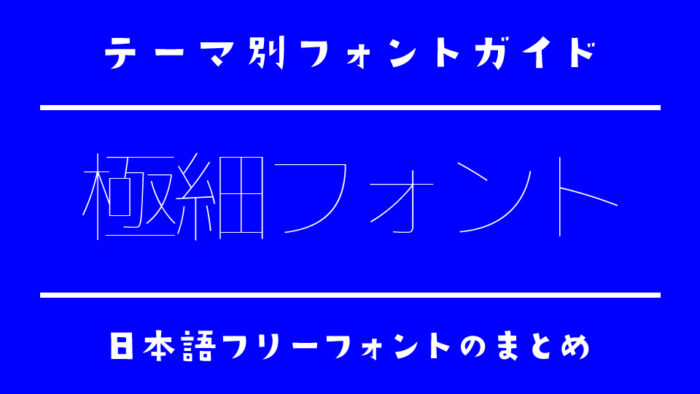
今回は、繊細でスタイリッシュな印象を与える「極細ウェイト」の日本語フリーフォントをご紹介します。
極細のラインは、空気のような軽やかさと、凛とした美しさを併せ持ち、シンプルな中にも上品さを演出してくれます。ミニマルなデザインや洗練された印象を求める場面にぴったりです。
今回は、そんな極細ウェイトの中でも、可読性とデザイン性を兼ね備えたフォントを厳選しました。ポスターやWebデザイン、名刺などのアクセントとして、ぜひ取り入れてみてください。
「極細ウェイト」のおすすめフォントまとめ
以下のサンプル画像は本記事で紹介している一部ですが、「極細ウェイト」をもつフォントをまとめてみました。
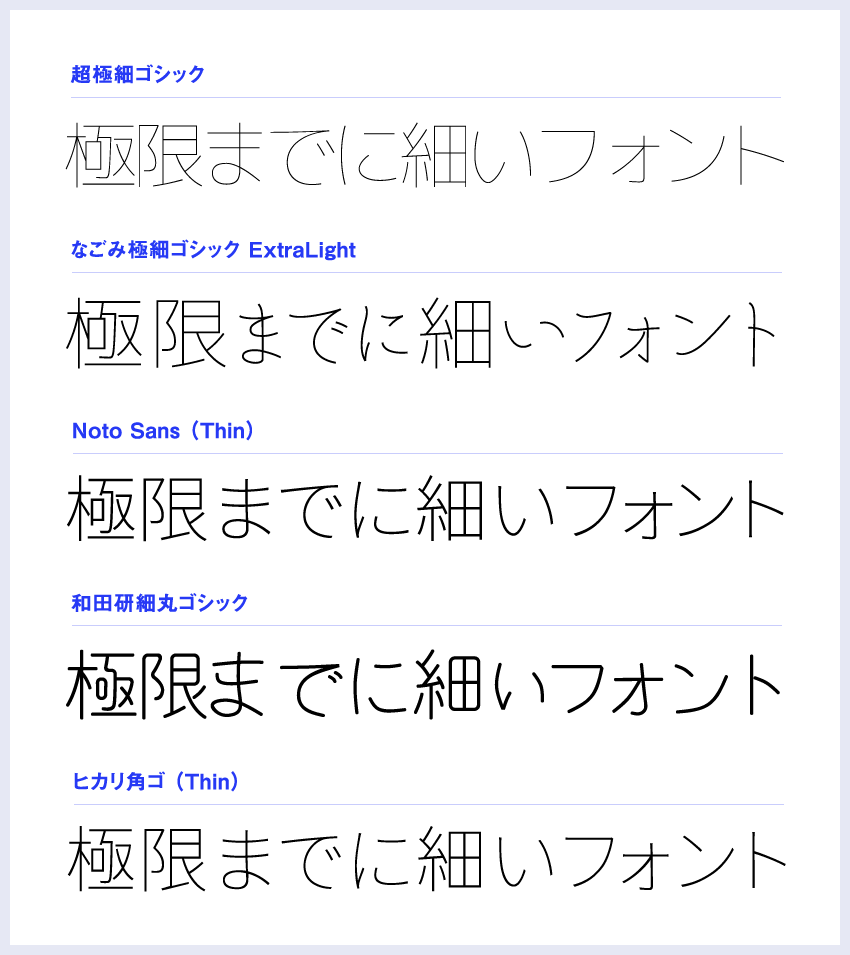
超極細ゴシック
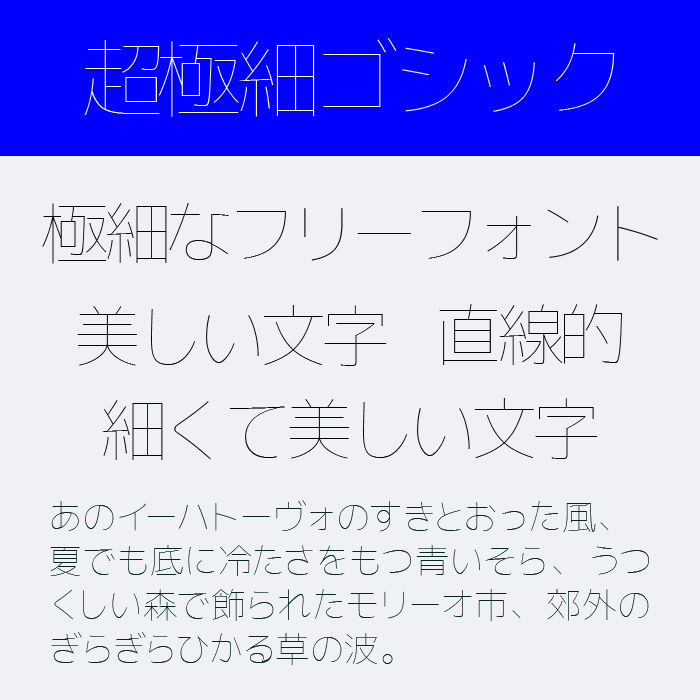
超極細ゴシック体フォントは、「超極細」を目的としてボールペンを使い定規でなぞって書いたようなイメージに制作されているゴシック体フォントです。
Noto Sans(源ノ角ゴシック)
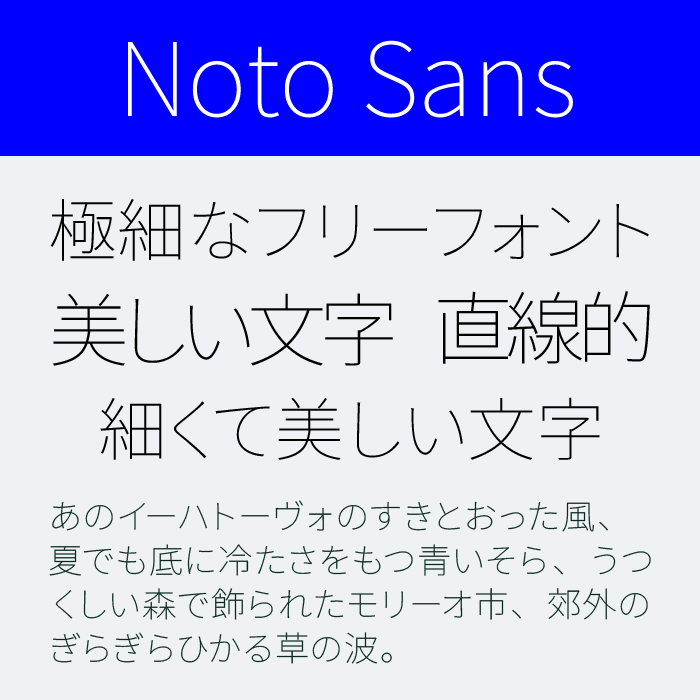
Noto Sans(源ノ角ゴシック)フォントは、GoogleとAdobeが協力して開発したベーシックな角ゴシック体フォントです。
世界中のあらゆる言語に対応することを目標に開発されているため、可読性や視認性に非常に優れているフォントです。一番細いウェイトが「Thin」ですが、可読性が優れてスタイリッシュな雰囲気あるフォントです。
ヒカリ角ゴ
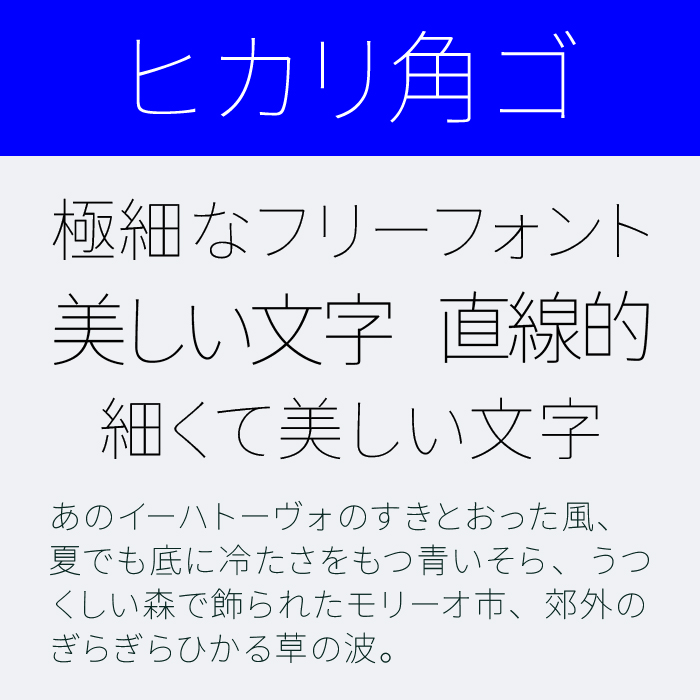
ヒカリ角ゴフォントは、上記の源ノ角ゴシック(Noto sans)をベースとして、ふところを狭く、漢字をより平らかになるように調整されたゴシック体フォントです。
ふところが調整されている分、直線的で機会的なクール雰囲気を感じるフォントです。
M PLUS
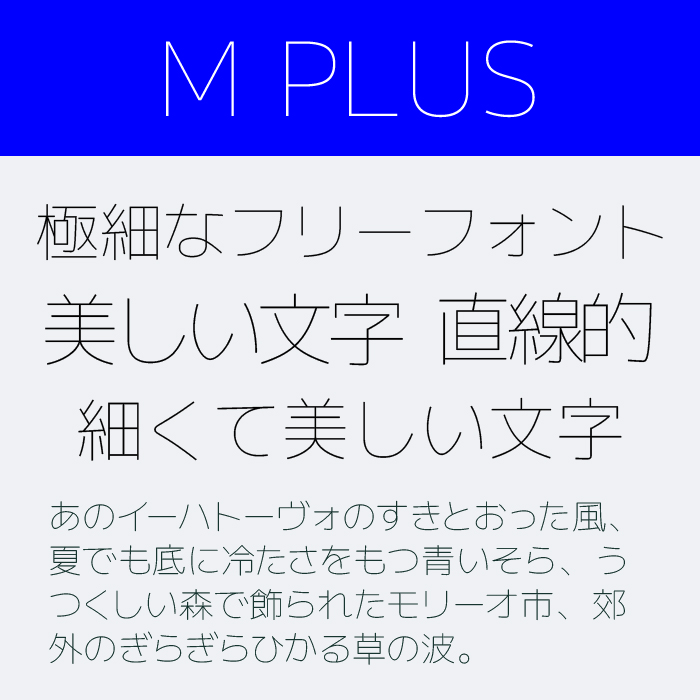
M PLUS(M+)フォントは、直線と曲線のメリハリがきいて、少し丸みがありカッチリしすぎていない、使いやすいモダンな角ゴシック体フォントです。ウェイトが9種類あり、一番細いウェイトが「Thin」です。
トガリテ
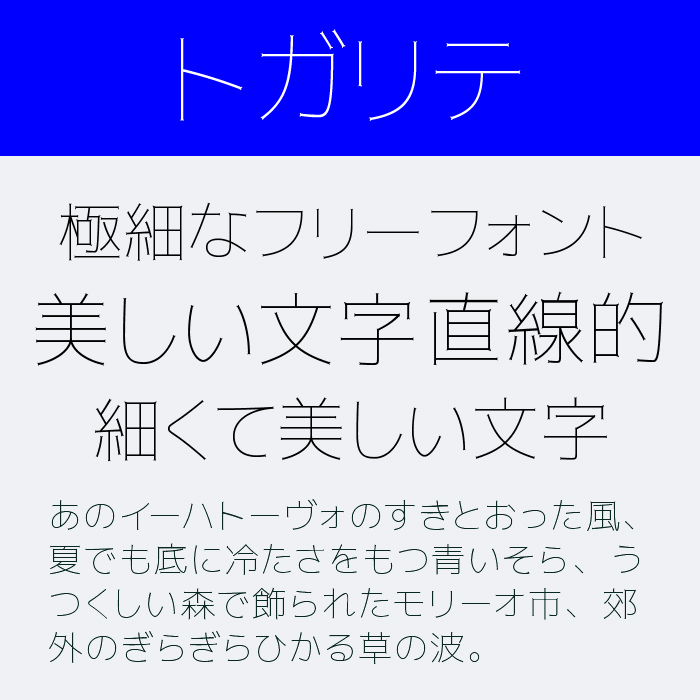
トガリテフォントは、文字の先端にトゲトゲの装飾が施されているフォントになっています。細いですが、線先に装飾が施されている可愛らしいフォントです。
和田研細丸ゴシック
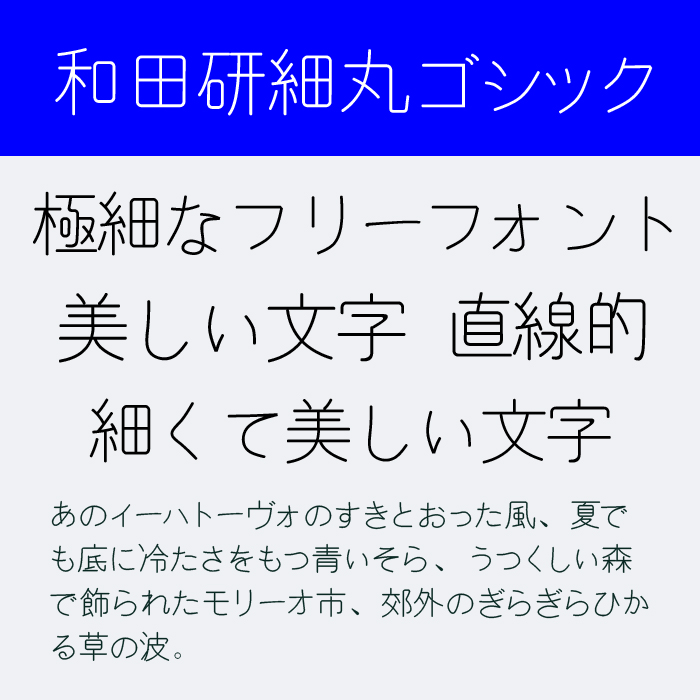
和田研細丸ゴシックフォントは、東京大学の学生による「和田研漢字分科会」が公開した丸ゴシックフォントです。
なごみ極細ゴシック
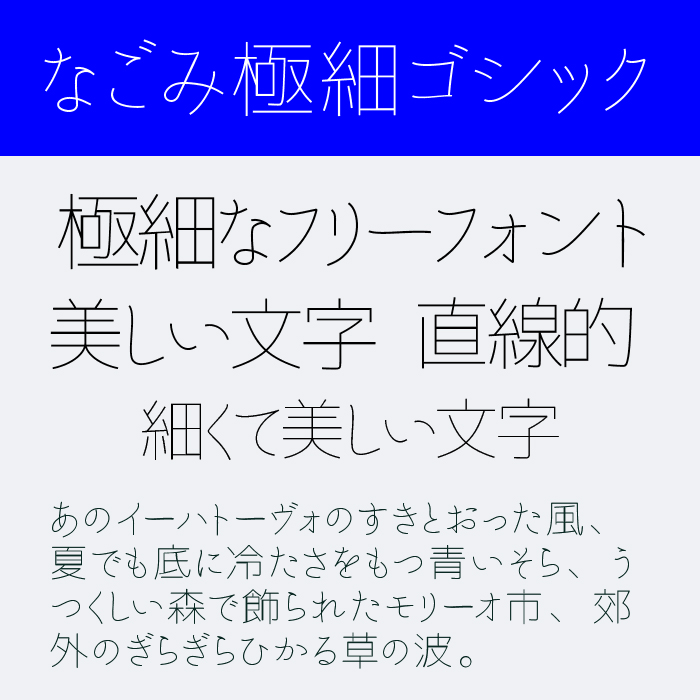
なごみ極細ゴシックフォントは、モダンで直線的な漢字デザイン、それとは対照的に懐が狭くオールドスタイルなかな文字デザイン、2つの特徴が合わさったユニークな日本語フォントです。